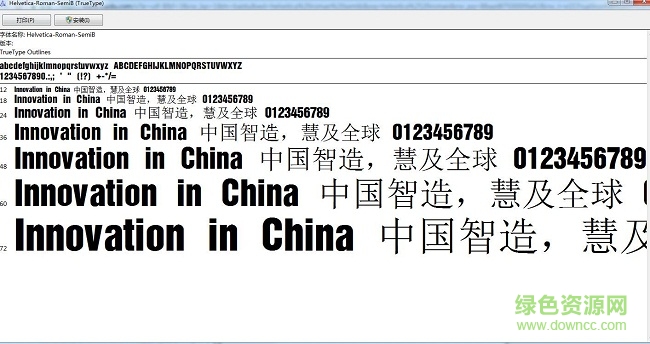
helvetica roman semib
helvetica roman semib字體是一款理性的現(xiàn)代無襯線字體,字間距緊湊,清晰易讀,識(shí)別性強(qiáng),沒帶什么感情,用在科技主題的設(shè)計(jì)或是商業(yè)海報(bào)領(lǐng)域是非常合適的,需要的朋友快來下載吧!
Helvetica字體涵義
Helvetica 可信、安全、實(shí)用、親和,極其條理化.......... 它代表了一種平凡的感覺,同時(shí)也意味著對日常的一個(gè)隱喻。
Helvetica 這個(gè)詞蘊(yùn)含著一種詩意的正直感:它既為富人服務(wù),也為窮人服務(wù);它既用在跨國公司的廣告,也用在本地快餐店的宣傳中;它準(zhǔn)確地傳達(dá)了瑞士精神的核心理念:中立。